27 款复古设计的最佳蒸汽朋克字体
已发表: 2022-04-15蒸汽朋克字体属于自己的一个类别。 这些富有创意、迷人、复古的字体融合了新旧字体,让人联想到维多利亚时代英格兰和美国狂野西部的形象。
它们创造了一种独特的美学,非常适合某些类型的科幻和奇幻书籍封面、电影海报和时装设计。
下面,我们列出了我们能找到的 27 种最好的 Steampunk 字体(免费和付费)。 这些字体一定会让你的创意工具呼啸而过。
什么是蒸汽朋克字体?
蒸汽朋克是科幻小说的一个子流派,灵感来自 19 世纪的时尚和蒸汽动力机械。 它将这种老式美学与科幻元素融为一体。 想想飞行护目镜、齿轮、煤炭、衬裙、礼帽和钟表。
蒸汽朋克已经演变成一种亚文化,激发了许多小说、游戏和电影。 这些创意作品通常设置在一个技术进步以蒸汽机为基础的反乌托邦世界。
蒸汽朋克字体是试图封装这种独特美学和亚文化的字体。 关于蒸汽朋克字体的外观并没有硬性规定,但它们通常具有以下特征:
- 维多利亚风格的设计
- 机械元件(齿轮、齿轮、管道等)
- 不寻常或装饰繁重的字体
27 种最佳蒸汽朋克字体
1.蒸汽朋克 3D 彩色字体——我们的首选
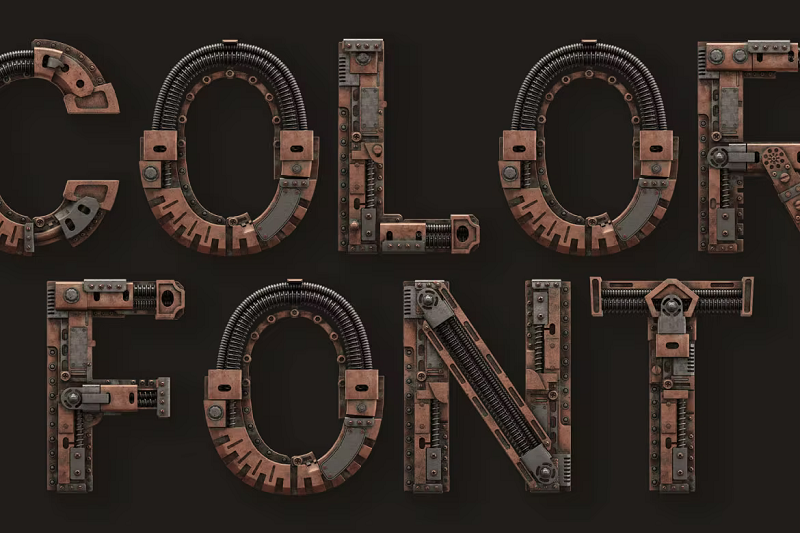
首先,我们有这款由 Cruzine 设计的非常详细的蒸汽朋克风格的 3D Color 字体。 像这样的彩色字体使用一种相对较新的字体格式,称为 OpenType SVG。 这种格式允许设计师在字体中加入更丰富的细节,如颜色、渐变和纹理。
这就是为什么这种字体能够看起来如此逼真以及为什么它具有如此酷炫的 3D 效果的原因。 缺点是您需要现代设计软件(如 illustrator 2018+ 和 Photoshop 2017+)才能正确打开此字体。
为什么它是我们的首选
在真正的蒸汽朋克风格中,这种字体看起来好像是由某些大型机器的联锁部件制成的。 3D 效果是超逼真的,让您的文本看起来就像是用螺栓、螺母和金属制成的。 没有比这更蒸汽朋克的了。
2.星舰
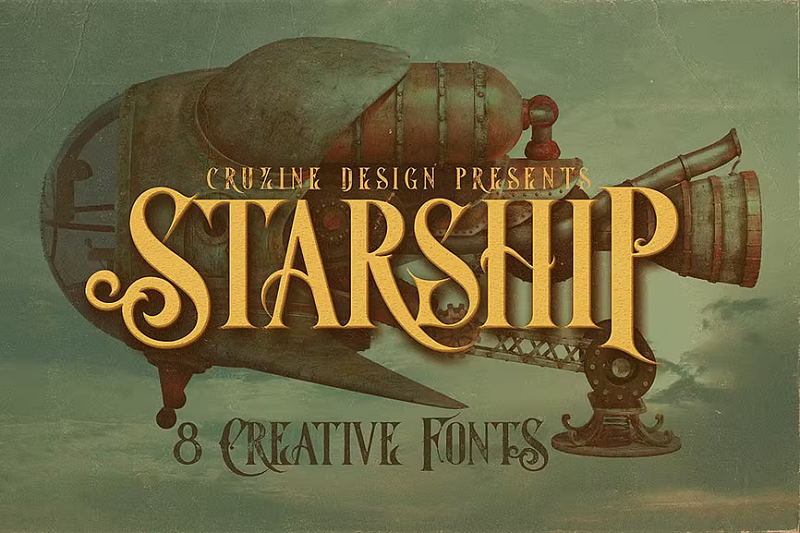
接下来,我们有 Cruzine 的另一种梦幻般的蒸汽朋克字体。 Starship 具有装饰性的复古字体,带有复杂的漩涡和古怪的花饰。 它有一丝优雅和个性。 你不能想象它印在某个虚构的土地上的神秘蒸汽动力飞行器的侧面吗?
3.章鱼
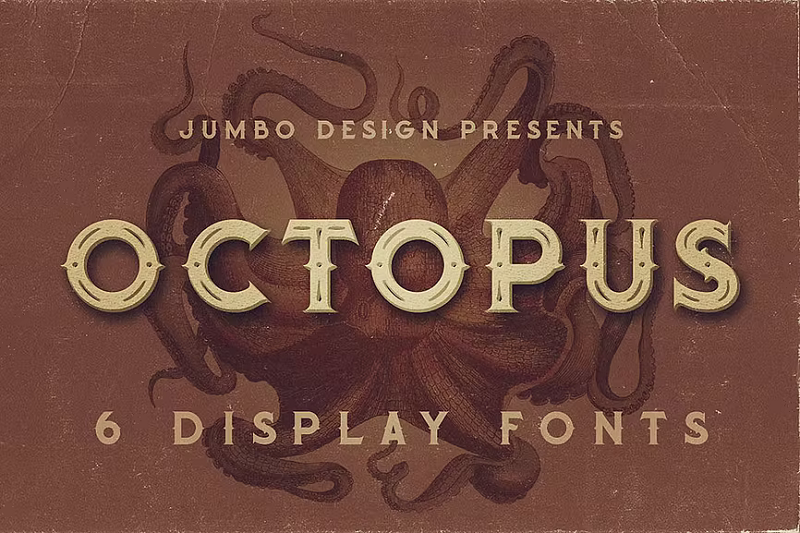
这是另一种独特的复古字体,具有明显的蒸汽朋克式美学。 它有六种样式:常规、垃圾、内联、内联垃圾、粗体和粗体垃圾。 Inline grunge 是我们个人的最爱。 纹理和复杂的细节使字体看起来非常独特。 Octopus 也是一种可读性很强的字体,因此它可以很好地用于标题和标题。
4.蒸汽朋克
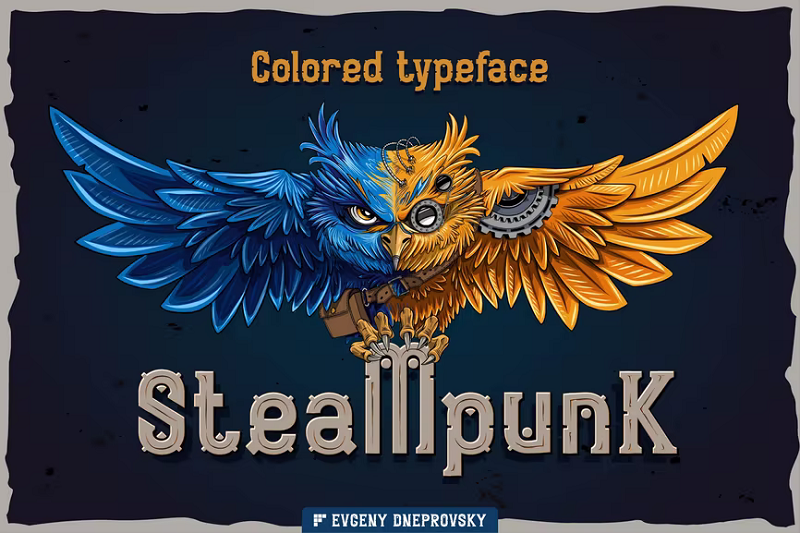
接下来,我们有 Fractal87 恰当命名的 Steampunk 字体。 这是一种整洁的、类似机器的字体,带有许多复杂的细节。 它有 5 种不同的款式:3 种黑色款式和 2 种彩色款式。 彩色版本是我们的最爱,并具有白色和铜色互锁齿轮的发条图案。
5.维多利亚时代的收藏
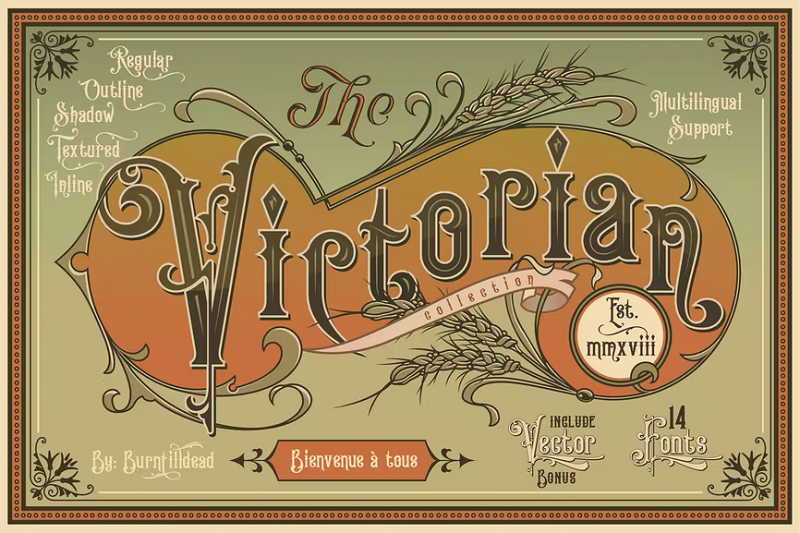
接下来,我们有一个庞大的维多利亚字体集合,会让你觉得你已经回到了 19 世纪。 这个巨大的包共有 1814 个字形。
该字体有两个主要版本:爱德华国王和伊丽莎白女王。 这两种维多利亚风格的字体都具有高度的装饰性和观赏性,因此它们在古典设计中效果很好。
每个还具有各种样式,包括常规、内联、轮廓、阴影和纹理。 您可以将多种样式叠加在一起,形成一个看起来很酷的分层组合,似乎跳出页面。
除了所有常用的字形之外,您还可以访问大量的替代品和 dingbats,您可以使用它们来为您的设计增添趣味。
6. Arbatosh 常规
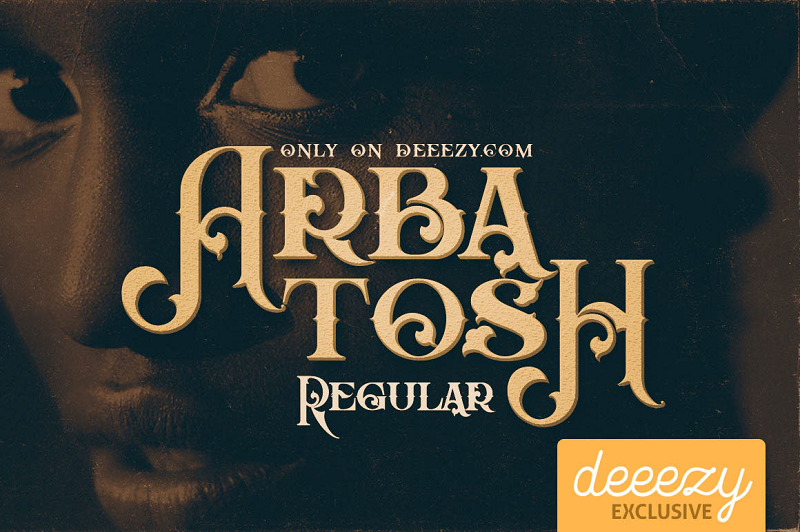
Arbatosh Regular 是一种具有装饰风格的独特复古字体。 它是免费提供的,有四种样式:常规、垃圾、内联和内联垃圾。 它非常适合标题和优雅的老式设计。
7.招牌店
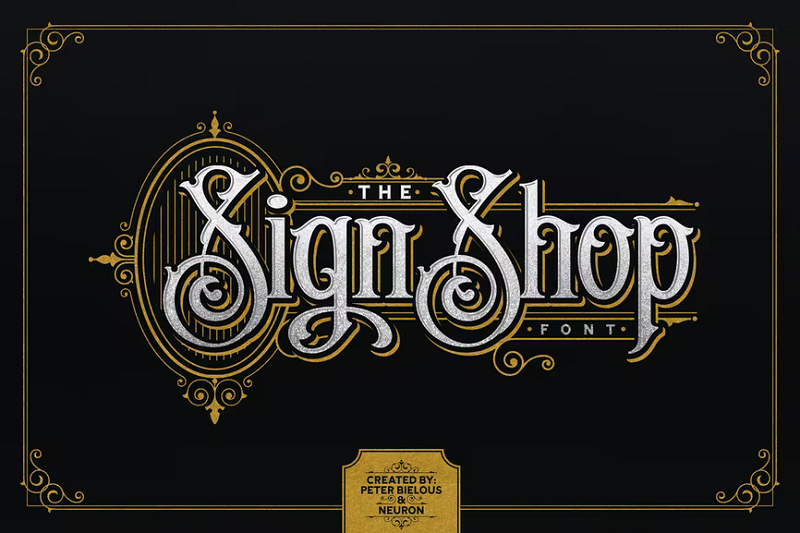
Peter Bielous 和 Neuron 的 Sign Shop 是我们个人的最爱之一。 这是一种受维多利亚时代启发的复古字体,具有许多装饰细节。 你不只是喜欢's'字形上那个长长的环形尾巴吗?
顾名思义,设计师还从复古标志中汲取灵感,所以如果您正在为古董店或类似的东西制作标志,这将是一个不错的选择。 它还带有一种名为 Old Taverna 的奖励字体,它与它非常搭配,以及矢量装饰品来完成您的设计项目。
8.星体
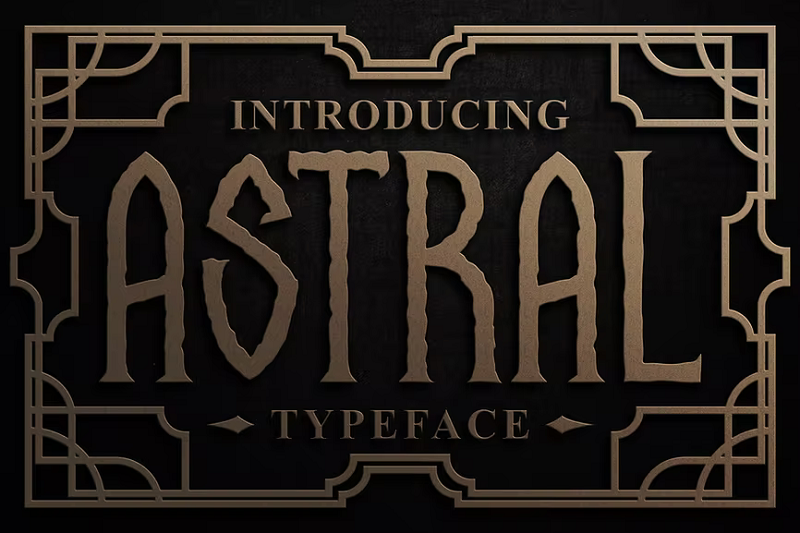
Astral 是另一种有趣的蒸汽朋克字体。 灵感来自天体的设计融合了复古和未来主义元素,采用波浪形笔触和高而窄的字体。 这是一种带有数字和标点符号的全大写字体。 它可以用于各种设计,但特别适合科幻电影海报和游戏等科幻主题。
9.埃莫吉内
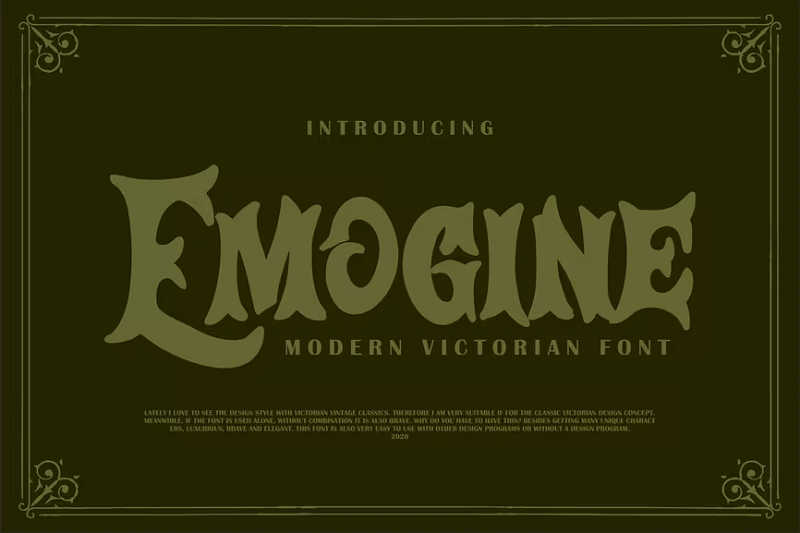
Emogine 是维多利亚时代的字体,由设计师 Vunira 设计,具有现代风格。 这是一种带有书法风格字形的手绘字体,在许多不同类型的设计上看起来都不错。
10.维多利亚式客厅
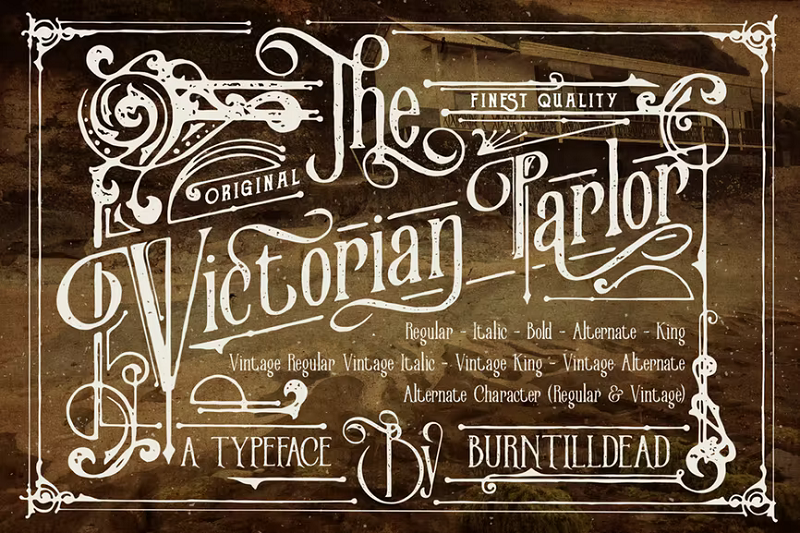
这是 Burntilldead 的另一个广泛的维多利亚字体包。 字体系列包括大量不同的样式,包括 Regular、Italic、Bold、Vintage(墨水纹理)、Alternate、King 等。总共有 350 多个字形。 此外,您还可以获得带有时尚图形的奖励复古矢量包,包括指南针、挂锁、钥匙和其他装饰元素。
11.马林
Marin 是由 cruzine 设计的六种经典维多利亚字体的集合。 风格包括常规、垃圾摇滚、阴影、阴影垃圾、维多利亚时代和维多利亚时代的垃圾(我们最喜欢的)。 字体简单干净,带有装饰性衬线。
12.蒸汽沉船
Steamwreck 是 Pixel Sagas 开发的一款出色的免费蒸汽朋克字体。 它具有受狂野西部启发的又高又薄的字体。 锻铁效果和加工细节创造了我们正在寻找的蒸汽朋克美学。 它有四种样式:常规、粗体、斜体和粗斜体。
13.铁马
Iron Horse 是另一种受维多利亚时代启发的字体。 它具有经典的复古设计和复杂的细节。
14.铜管
这是另一种很棒的 3D 彩色字体,可以在您的下一个蒸汽朋克设计项目中尝试。 这些字形看起来好像是由互锁的铜管构成的; 您可能会在老式蒸汽动力机械中找到那种。
15.维多利亚时代的霸权
Burntilldead 又回来了,带来了另一个令人难以置信的维多利亚风格字体包。 Victorian Supremacy 的灵感来自 19 世纪末的信笺抬头。 它庄严,优雅,非常高雅。
下载包非常广泛,可让您访问大量字形。 有四种主要风格和几个分层版本。 除了拉丁字母、数字和标点符号外,它还附带大量替代品,以及可添加到设计中的全矢量化丝带、面板和其他插图的奖励包。
16.发条
Clockwork 是 Maulana Creative 的一款黑色字体,非常适合蒸汽朋克设计。 哥特式风格和深色、饱和的字体可以追溯到 1800 年代初期。 它提供了对维多利亚时代经典手工艺的现代诠释
17.神话般的蒸汽朋克
神话般的蒸汽朋克看起来像是直接来自宫崎骏的电影。 它体现了蒸汽朋克的精髓,并带有大量华丽的细节。 每一个字形都是独一无二的,代表着一台不同的、神秘的机器。
有齿轮在呼呼,管道滚滚蒸汽,链条在每个字母上隆隆作响。 你可以整天盯着这个字体,永远不会觉得无聊。 它充满了视觉趣味,使其成为各种创意设计的绝佳选择。 最好的部分是什么? 免费!